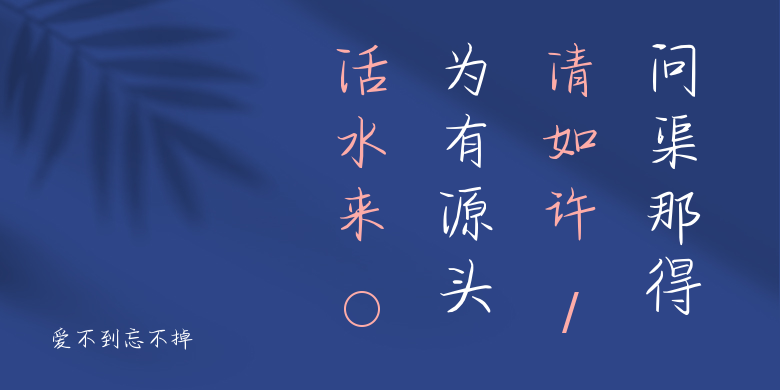
爱不到忘不掉
爱不到忘不掉,这款字体结构工整、笔画清晰,兼顾美观与易读性,适用于标题、正文、海报、包装、LOGO 等多种场景。字形优雅稳定,风格百搭耐看,适配日常排版与创意设计,让文字呈现更舒适、更具质感。爱不到忘不掉一笔一画,皆是细节,以均衡的比例、流畅的线条打造舒适视觉体验,字形端正大气,风格简约现代。无论是商业设计、品牌宣传还是日常排版,都能轻松驾驭,让文字更有格调与力量。爱不到忘不掉字体下载。